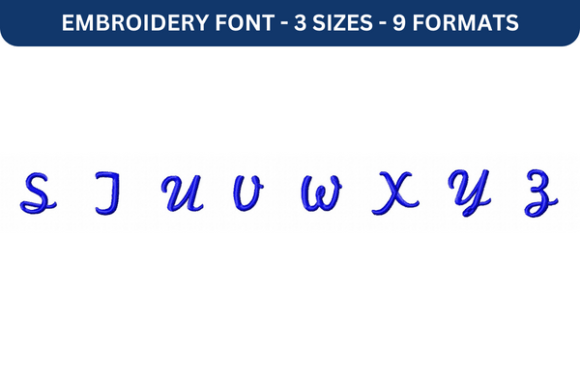
Marketing Script Font Upper S to Z
Mencari elemen reka bentuk yang sesuai boleh menjadi mencabar, tetapi Marketing Script Font Upper S to Z menawarkan koleksi luar biasa yang menaik taraf karya anda serta-merta.
Dicipta dengan ketepatan, Marketing Script Font Upper S to Z menyediakan vektor yang bersih, tipografi yang licin dan lesen komersial untuk ketenangan fikiran.
Sama ada anda mencipta produk POD (Print on Demand), jemputan perkahwinan atau grafik media sosial, Marketing Script Font Upper S to Z amat bersesuaian.